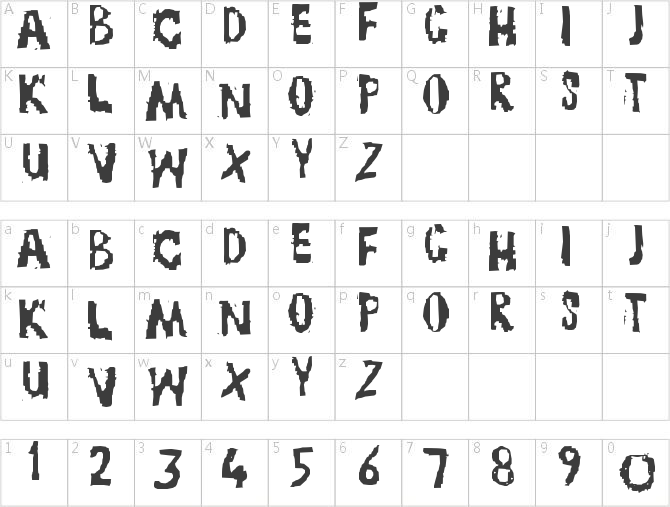
TRUCK NOVEMBRE GRUPPE
TRUCK NOVEMBRE GRUPPE介紹
TRUCK NOVEMBRE GRUPPE字體字庫是一款讓人賞心悅目、百看不厭的英文字體,適合各類廣告和產(chǎn)品包裝設計應用,字體大小0.03MB,格式為ttf字體,上傳用戶是Elieen,作者/版權方為未知